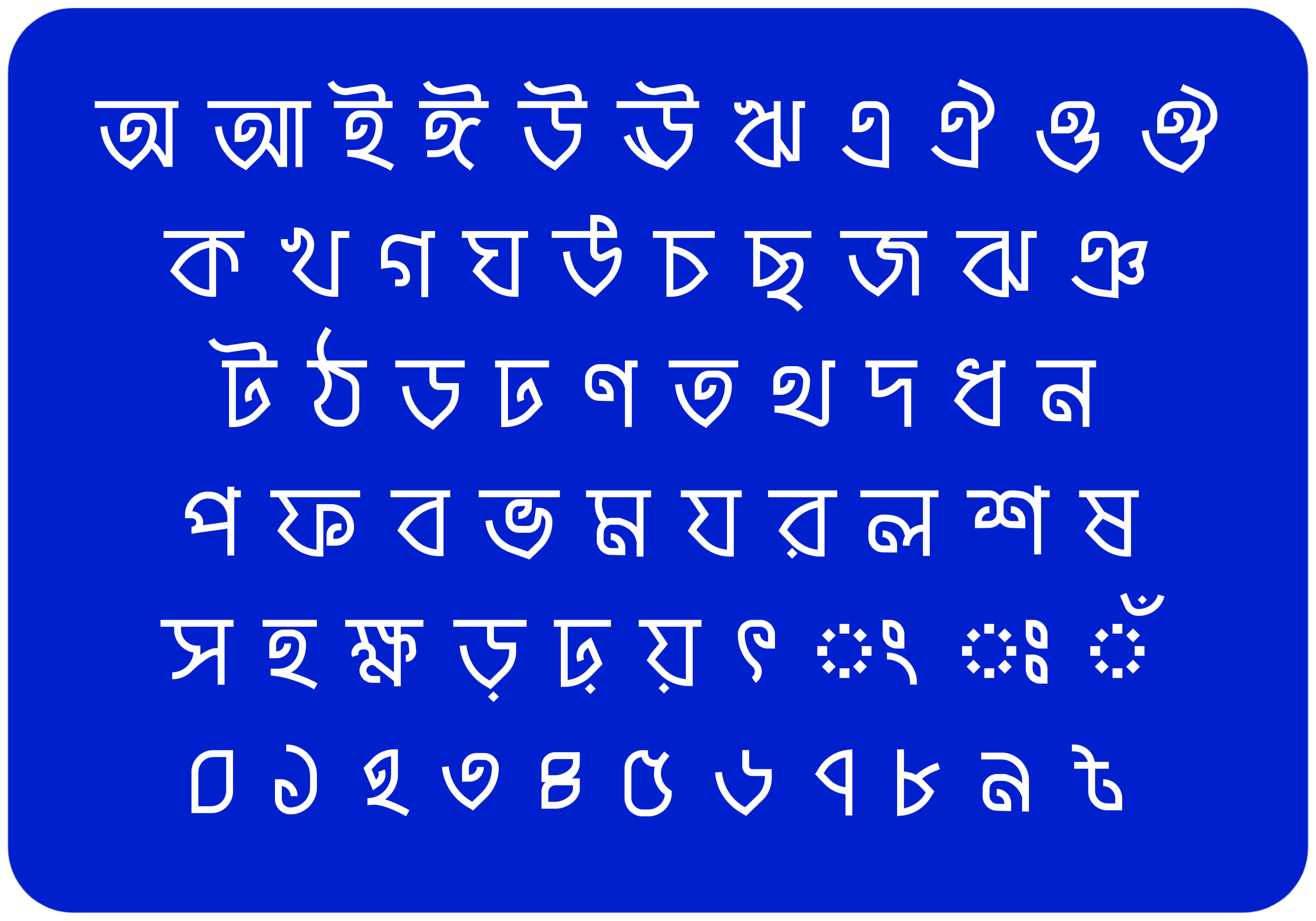
ইমন বর্ণবলয় মূলত একটি প্যারাগ্রাফ বাংলা ফন্ট। এই ফন্টটি যেকোনো ধরণের প্যারাগ্রাফ টেক্সটে ব্যবহার করতে পারবেন। এছাড়া স্ট্যাটাস ভিডিও তৈরির ক্ষেত্রে এই ফন্টটি বিশেষভাবে ব্যবহারযোগ্য। বাংলা টাইপোগ্রাফি এর জন্যও আপনি এই ফন্টটি ব্যবহার করতে পারবেন।
ইমন বর্ণবলয়
- নকশাকার : ইমন হাসান
- বিকাশকারী : ইমন হাসান
- রূপ : ১ টি
- বর্ণের ভাষা : বাংলা